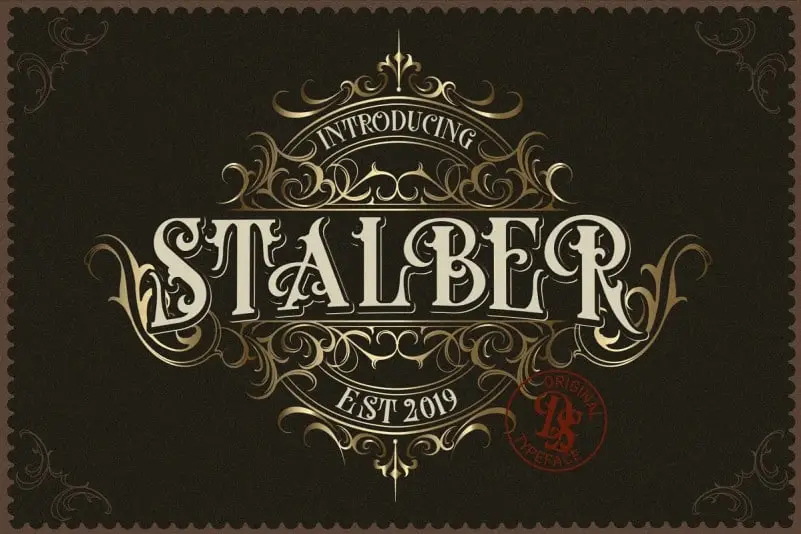
Stalber Blackletter Font – Download Grátis
A fonte ‘Stalber Blackletter Font’ é uma tipografia moderna que transmite a essência vintage. Criação do designer danseD, essa fonte utiliza referências a diferentes letras para combinar e desenhar com seu estilo próprio. Perfeita para adicionar um toque de nostalgia ao design de sites antigos, livros de histórias épicas ou até mesmo anúncios vintage. A estética moderna e as nuances vintage desta font criam uma harmonia única que cativa o olho do designer e do leitor. Seja você um apaixonado por tipografia ou simplesmente deseja dar um toque especial à sua marca ou projeto, a ‘Stalber Blackletter Font’ da 99designs é certamente a opção ideal para seu próximo projeto.